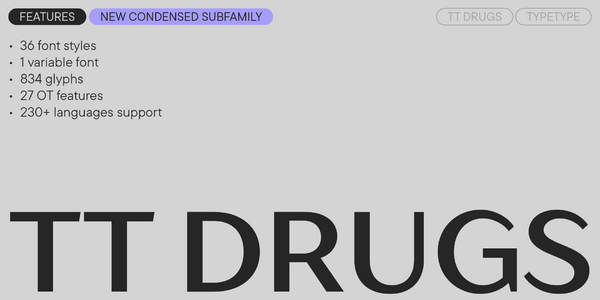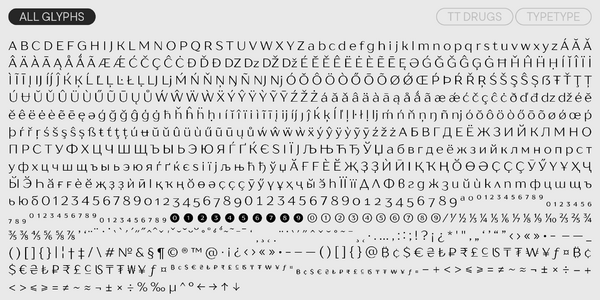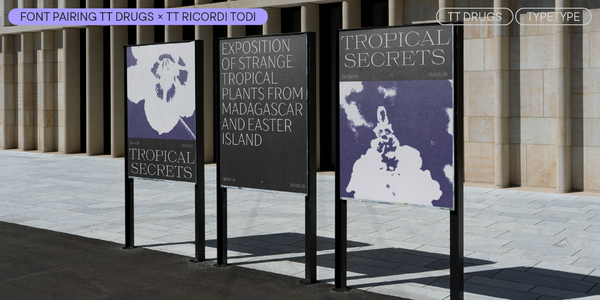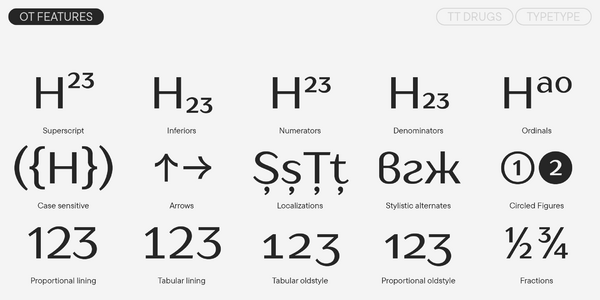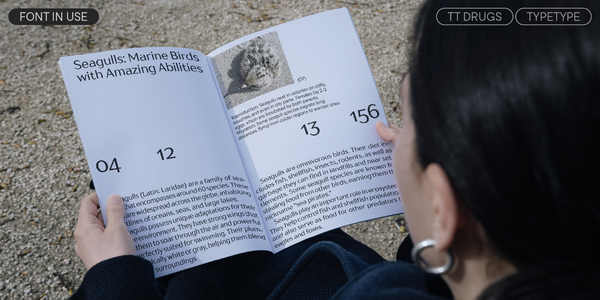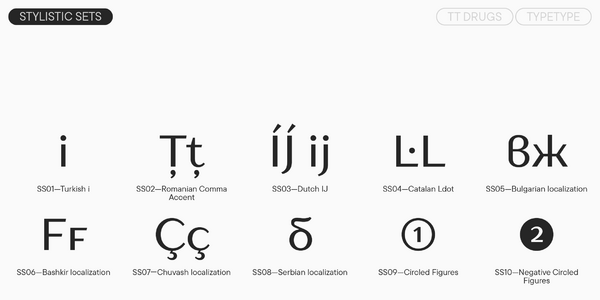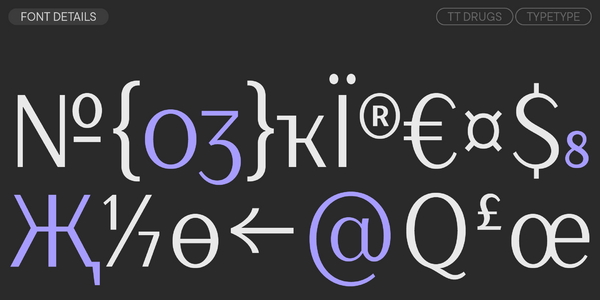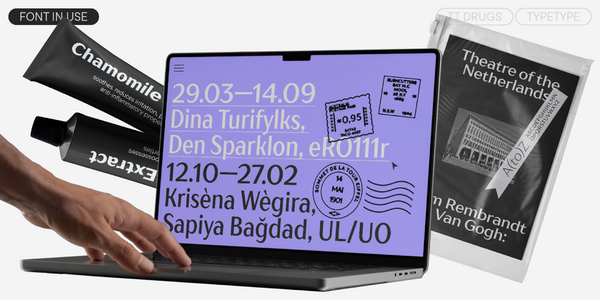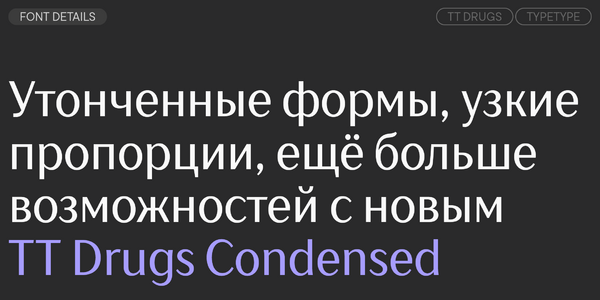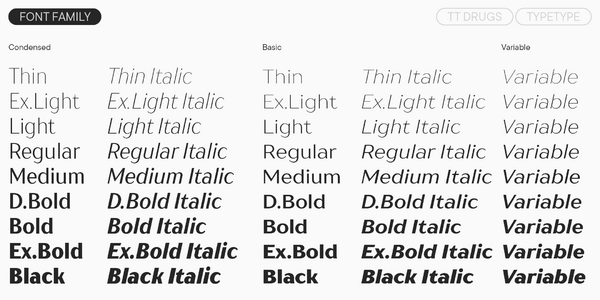
TT Drugs
TT Drugs — ТТ Драгс
Произносится «ТТ Драгс». «Drugs» — производное слово от drug, в переводе с английского «медикамент, лекарство». Буквы «TT» являются аббревиатурой названия компании.
TT Drugs — изысканная и одновременно серьёзная ленточная антиква. Шрифт универсален в применении.
Вторая версия ленточной антиквы TT Drugs: «подлечили» шрифт от старых недугов
В далеком 2015 году, когда мы начинали проектировать шрифтовое семейство TT Drugs, мы предполагали, что оно будет использоваться в основном в фармацевтической промышленности. Это было связано с тем, что данный тип шрифтов широко распространен именно в фармацевтике: например, применяется на упаковках медицинских препаратов и лекарств. К этой же категории мы отнесли производителей бытовой химии, которые выпускают зубные пасты, шампуни, стиральные порошки и средства детской гигиены. Именно отсюда взялось игривое название шрифта.
Лекарство от всех болезней
За 8 лет существования шрифта мы увидели, что наши клиенты используют его в совершенно разных проектах. Например, в брендинге различных объектов недвижимости по всему миру, на всевозможных упаковках и обложках книг. Осознав огромный потенциал гарнитуры, мы решили дать «старичку» вторую жизнь. В 2023 году мы начали перерисовывать шрифтовое семейство. Улучшили контуры всего шрифта (фактически перерисовали их полностью). Пересчитали все пропорции шрифта, тем самым увеличив потенциальные сферы его использования. И, конечно же, добавили новые начертания. Шрифт получил расширенную кассу знаков, обновленный хинтинг и кернинг. Мощные инъекции молодости для нашего классного TT Drugs!
Большое обновление случилось в 2025 году — появилось Condensed подсемейство
О гарнитуре TT Drugs
Встречайте легендарный TT Drugs версии 2.100!
Сделали шрифту «укол красоты»: добавили новое подсемейство, дополнили вариативный шрифт и усовершенствовали техническую составляющую.
TT Drugs — ленточная антиква: это шрифт без засечек и с выраженным контрастом. Благодаря зауженным терминалам он выглядит элегантно и утонченно. Интересно, что верхние части стемов в буквах «n», «m», «p», «q», «r» и нижние элементы штрихов в «a» и «u» слегка изогнуты — эти детали делают шрифт уникальным и придают ему изысканность, не мешая оставаться серьезным.
Название гарнитуры напоминает об истории её создания: изначально семейство разрабатывалось специально для использования в фармацевтической промышленности. Однако на практике шрифт показал, что может быть гораздо более разносторонним и гармонично вписываться в проекты с совершенно разной тематикой. А после обновления стал еще более универсальным, так что теперь о медицинском прошлом TT Drugs напоминает только его провокационное название.
Так, обновленный шрифт может стать частью визуального образа бренда уходовой косметики, украсить обложку журнала о дизайне интерьеров, использоваться на вывеске ресторана здорового питания или в афише классического концерта.
Мы полностью перерисовали TT Drugs: пересчитали развесовку, сделали графику более звенящей, чистой и современной. Критически переосмыслили кириллические формы и убрали неоднозначные решения. В версию 2.100 мы добавили подсемейство Condensed, состоящее из 18 начертаний — 9 прямых и 9 наклонных. Также мы добавили в вариативный шрифт ось Width (ширина), так что теперь он способен меняться по всем трём осям. А ещё — обновили кернинг и хинтинг.